Fonturi web: cum să le faci să funcționeze perfect în e-mail
Publicat: 2021-04-24Din studiul meu foarte științific (am observat-o pe fiica mea când a început să scrie rapoarte în ultimul an), am învățat că unul dintre primele aspecte ale designului cu care oamenii încep vreodată să se joace este tipografia. Când începeți să scrieți rapoarte, petreceți ore întregi încercând să găsiți cel mai bun font de utilizat. Ok, poate nu ore, dar majoritatea oamenilor petrec puțin timp pe asta. Pentru că, după cum știu marile mărci, tipografia contează. Și contează în e-mail.
Dar și accesibilitatea contează. Așa că nu mai prindeți mesajul în imagini și începeți să utilizați text live cu fonturi sigure pentru web și fonturi web. La urma urmei, textul care nu depinde de imagini și poate fi citit de un public mai larg duce la o experiență excelentă pentru abonați. Și, în calitate de cei mai buni clienți ai tăi — e-mailul returnează 36 USD pentru fiecare dolar investit — asta este grozav pentru strategia ta generală de marketing.
Fonturi web versus fonturi sigure pentru web
Există două moduri diferite în care puteți face text live: fonturi sigure pentru web și fonturi web. Deși sună la fel, există diferențe clare. Pentru a înțelege aceste diferențe, să aruncăm o privire la modul în care funcționează fonturile în e-mailurile tale.
Când e-mailul dvs. este codificat, fontul este declarat folosind o proprietate CSS numită font-family. Această proprietate a familiei de fonturi poate avea un singur nume de font sau mai multe nume de fonturi, adesea denumite stivă de fonturi. Includerea mai multor nume de font vă asigură că, dacă un font nu funcționează, există un font alternativ sau de rezervă, la alegerea dvs. Fără a enumera mai multe nume de fonturi, clientul de e-mail poate decide fontul de rezervă. Când abonații vă deschid e-mailul, browserul citește proprietatea familiei de fonturi și trage fontul pentru a-l utiliza.
Fonturi sigure pentru web
Cu fonturi sigure pentru web, browserul extrage fontul din directorul local de fonturi. Aceasta înseamnă că acestea sunt fonturi care sunt deja instalate pe computer. Toate computerele vin cu fonturi preinstalate, iar acestea sunt ceea ce este considerat sigur pentru web. Acestea sunt sigure , deoarece există o șansă foarte bună de abonat va avea deja ei, de asemenea.
Dezavantajul este că există un număr limitat de fonturi sigure pentru web în comparație cu fonturile web. Și sunt folosite destul de des, așa că este mai puțin probabil să ieși în evidență (dacă asta țintiți).
Fonturile sigure pentru web sunt:
- Arial
- Helvetica
- Verdana
- Georgia
- Times New Roman
Dar există câteva altele pe care le poți folosi cu un anumit grad de încredere. Așadar, ieși din bucla standard de font Arial sau Helvetica și găsește un font sigur pentru web, care funcționează pentru marca ta.
Cea mai bună resursă pe care am găsit-o pentru fonturile sigure pentru web este Fonturile CSS. Îmi place că includ un procent de utilizare pentru PC-uri și Mac-uri pentru fiecare font, astfel încât să știți aproximativ câți dintre abonații dvs. ar putea vedea fontul dorit și câți vă vor vedea alternativ.
Fonturi web
Fonturile web sunt extrase de pe un server, fie unul pe care îl găzduiți dvs., fie unul extern (cum ar fi Google sau Adobe). Din acest motiv, varietatea de fonturi care pot fi utilizate este mult mai mare și pot fi folosite pe orice computer... atâta timp cât browserul sau clientul de e-mail poate introduce fontul. În unele cazuri, abonatul dvs. poate avea deja un web font descărcat și instalat pe computerul lor, astfel încât aceste fonturi vor funcționa chiar și în clienții de e-mail care nu acceptă fonturi web!
Deci, în timp ce fonturile web vă oferă mult mai multă varietate și libertate creativă, ele au un cost: suport limitat pentru clientul de e-mail (în care mă aprofundez mai jos).
De ce fonturi web?
Deci s-ar putea să vă întrebați, de ce să vă deranjați cu fonturile web? În calitate de marketer și designer, cunoașteți presiunea de a rămâne pe brand în e-mail cu culori, design și — da — tipografie. Fonturile web vă permit să vă prezentați marca fără a vă baza pe imagini pentru textul dvs.
Blocarea unei copii importante în imagini a fost o practică standard în designul de e-mail, ca o modalitate de a rămâne pe brand și de a fi creativ. Dar „ascunderea” textului din imagini limitează accesibilitatea e-mailului, deoarece cititorii de ecran nu pot citi textul de pe imagine.
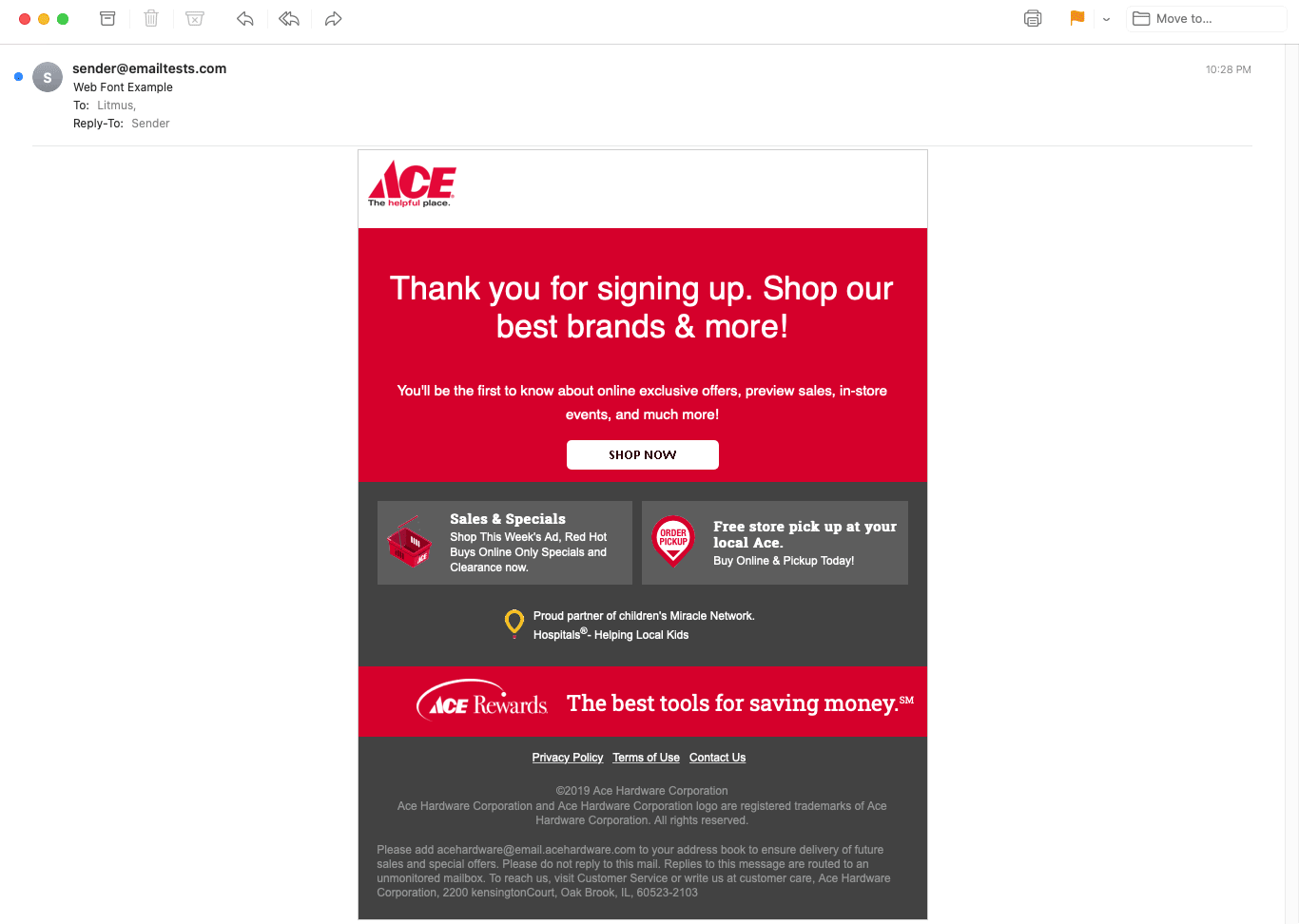
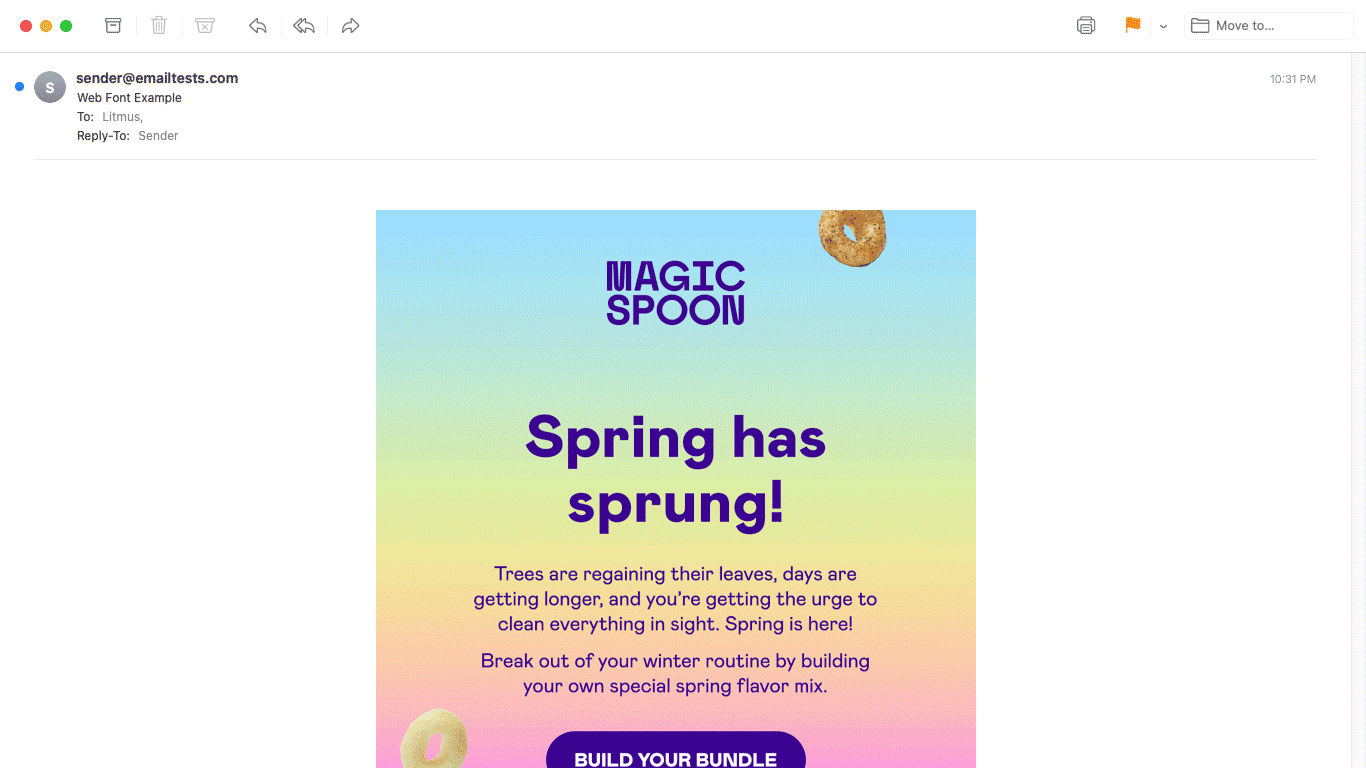
Și, dacă aveți text în imaginile dvs., dăunează experienței abonaților dacă au imaginile dezactivate în mod implicit. Este posibil ca aceasta să nu fie o mare parte a abonaților tăi, dar chiar nu există nicio modalitate de a ști dacă cineva are imaginile dezactivate și deschide e-mailul tău. Deci, de ce să nu oferi cea mai bună experiență pentru cel mai larg public posibil?
Fonturile web deschid noi căi de creativitate în tipografie, permițând designerilor de e-mail să fie creativi și accesibili – și să rămână la aspectul mărcii lor.
Pot folosi fonturi web în e-mail?
Dacă nu ai ghicit deja, răspunsul este da! Dar, ca și în toate lucrurile prin e-mail, există avertismente.
Asistență client prin e-mail
Fonturile web funcționează doar în unii clienți de e-mail și trebuie avut grijă să vă asigurați că acolo unde nu sunt acceptate, fontul cade înapoi cu grație.
| Client de e-mail | Suport pentru fonturi web |
|---|---|
| Apple Mail | ✓ Da |
| Outlook 2007-2016 | ✘ Nu |
| Outlook 2019 | ✘ Nu* |
| Outlook pentru Mac | ✓ Da |
| Outlook Office 365 | ✘ Nu* |
| Aplicația Gmail | ✘ Nu* |
| iOS | ✓ Da |
| Aplicația Outlook | ✘ Nu |
| Samsung Mail | ✘ Nu* |
| AOL Mail | ✘ Nu |
| Gmail | ✘ Nu* |
| Office 365 | ✘ Nu |
| Outlook.com | ✘ Nu |
| Yahoo! Poștă | ✘ Nu |
*Are unele rezultate neplăcute în funcție de metoda de încorporare a e-mailului, discutată mai târziu.
Merită să aruncați o privire la baza dvs. de abonați pentru a vedea câți vă văd e-mailurile într-un client de e-mail care acceptă fonturi web. Dacă sunt suficienți dintre abonații tăi, atunci este o modalitate minunată de a-ți oferi e-mailului o notă suplimentară.
Dacă majoritatea nu sunt, pur și simplu nu ar merita timpul și efortul dvs., mai ales dacă vă gândiți să utilizați un font web plătit.
![]() | Ce clienți de e-mail folosesc abonații tăi ? Aflați unde vă deschid abonații e-mailurile și cum interacționează, cu Litmus Email Analytics. Obțineți informațiile de care aveți nevoie pentru a vă optimiza e-mailurile și nu numai. Aflați mai multe → |
Licențiere
Fonturile web au fost concepute inițial pentru a fi utilizate exclusiv pe site-uri web, astfel încât licențele lor sunt de obicei utilizate numai pe site-uri web și aplicații mobile. Motivul pentru care multe servicii de fonturi web nu au permis utilizarea în e-mail este că acesta este considerat ca distribuirea fontului, ceea ce contravine Acordului de licență pentru utilizatorul final (EULA) al multor servicii.
Toți furnizorii de fonturi web pe care i-am contactat au acceptat utilizarea fonturilor lor în e-mail. Fiecare furnizor avea o licență diferită care era necesară, așa că nu există un mod standard în care fonturile sunt licențiate în e-mail. Dacă doriți să utilizați un font, contactați compania pentru a afla exact cum își licențiază fonturile.
Unde găsiți fonturi web
Așa că ați gândit totul și ați decis că doriți să încercați fonturile web. Cu opțiuni aparent nesfârșite, le puteți găsi pe cele care să se potrivească mărcii dvs. Dar este, de asemenea, important să țineți cont de accesibilitate.
Unele fonturi sunt mai ușor de citit decât altele.
Fonturile ornate sau decorative, cum ar fi fonturile de afișare sau de scris de mână, pot face dificil pentru persoanele cu deficiențe de vedere sau dislexie să facă diferența dintre formele literelor. Fonturile sans-serif (fonturi fără caracteristici extinse sau bucle în literele lor, cum ar fi Arial, Calibri, Century Gothic sau Helvetica) și fonturile slab (fonturi cu linii mai groase, cum ar fi Museo Slab și Rockwell) sunt considerate mai accesibile.
Iată câteva locuri bune în care să începeți să căutați.
Fonturi Google
Există o mulțime de servicii de fonturi web disponibile, dar Google Fonts este preferatul nostru. Serviciul este complet gratuit și puteți descărca fonturile web pe computer dacă faceți joc de modele în Adobe Photoshop, Sketch sau alt software de design.
Fonturi Adobe
Typekit a devenit Adobe Fonts din octombrie 2018. Aceștia acceptă acum atât metoda <link>, cât și metoda @import pentru utilizarea fonturilor ca fonturi web (mai multe despre asta în continuare). Serviciul nu este complet gratuit, dar dacă aveți deja un abonament Creative Cloud, este inclus cu acesta.
Servicii de fonturi web
Există mai multe alte servicii de fonturi web disponibile pe bază de plată. Va trebui să vă asigurați că obțineți licența corectă pentru a le folosi în e-mailul dvs.
- Tip Rețea (licență web)
- Tip de proces Turnătorie (licență web)
- Optimo (licență pentru anunțuri digitale)
- Fontspring (licență de e-mail personalizată)
- Typotheque (licență web)
- Tip de producție (licență de publicitate online)
- MyFonts (licență web)
- Tip comercial (licență web)
Cu licențele web, poate exista posibilitatea de a găzdui fontul singur sau de a avea fontul găzduit de furnizor. În unele licențe web, plătiți pentru o anumită cantitate de vizualizări de pagină cu fiecare e-mail care încarcă fontul numărând ca vizualizare de pagină, așa că asigurați-vă că luați în considerare acest lucru atunci când achiziționați o licență.
Cum să încorporați fonturi web în e-mailuri
Deoarece fonturile web de obicei nu se găsesc pe dispozitivul local al cuiva și sunt găzduite în altă parte, mai întâi trebuie să „încorporați” sau să importați fontul web în e-mailurile dvs. înainte de a le putea folosi efectiv.
1. Obțineți adresa URL a fișierului fontului dvs
Veți avea nevoie de adresa URL a fontului dvs. web pentru a o apela în e-mailul dvs. Serviciul dvs. de fonturi web ar trebui să aibă această adresă URL. Dar dacă găzduiți singur fișierul cu font, obțineți adresa URL de unde se află fontul web pe serverul dvs. Asigurați-vă că este o adresă URL publică și nu provine de la un server local. În caz contrar, abonații dvs. nu vor putea accesa fontul web și vor vedea în schimb un font alternativ.
Dacă utilizați Fonturi Google, găsirea adresei URL este puțin dificilă, dar nu prea dificilă. Aflați cum în pasul următor pentru metoda de încorporare @font-face.
2. Importați fontul web utilizând una dintre cele trei metode
Există trei metode pentru încorporarea fonturilor web în e-mail (și o avertizare care poate limita metoda pe care o puteți utiliza). Cele trei metode de încorporare a fontului sunt:
- <link>
- @import
- @font-face
Deci de ce ai alege o metodă în detrimentul alta?
Metoda @import amână încărcarea fontului web care este importat până când HTML-ul în care este încorporat este încărcat complet. Acest lucru poate face ca fontul dvs. web să dureze ceva mai mult să apară în e-mail, în timp ce restul e-mailului este încărcat. În schimb, metoda <link> încarcă resursa în linie pe măsură ce se citește codul fișierului HTML (de sus în jos), ceea ce ar putea întârzia încărcarea e-mailului dacă fișierul cu fonturi web este deosebit de mare.
Un alt lucru de care trebuie să țineți cont atunci când alegeți o metodă de utilizat este ceea ce acceptă ESP.
Puteți crea un cod frumos care funcționează în Litmus toată ziua, dar dacă ESP vă schimbă codul, așa cum știm că fac majoritatea, atunci nimic din ce faceți nu va conta. Asigurați-vă că ESP nu vă modifică codul într-un mod care ar face ca fonturile să nu mai funcționeze. La Litmus, ESP-ul nostru nu ne permite să includem condiționale MSO în jurul elementelor de stil. Prin urmare, metodele <link> și @import nu vor funcționa pentru noi, deoarece nu sunt bine acceptate în Outlook, despre care vom discuta mai jos.
Folosind <link>
Folosirea metodei <link> este o metodă relativ simplă pentru încorporarea fonturilor în e-mailul dvs. Plasați această linie de cod în <head> e-mailului dvs., în partea de sus: